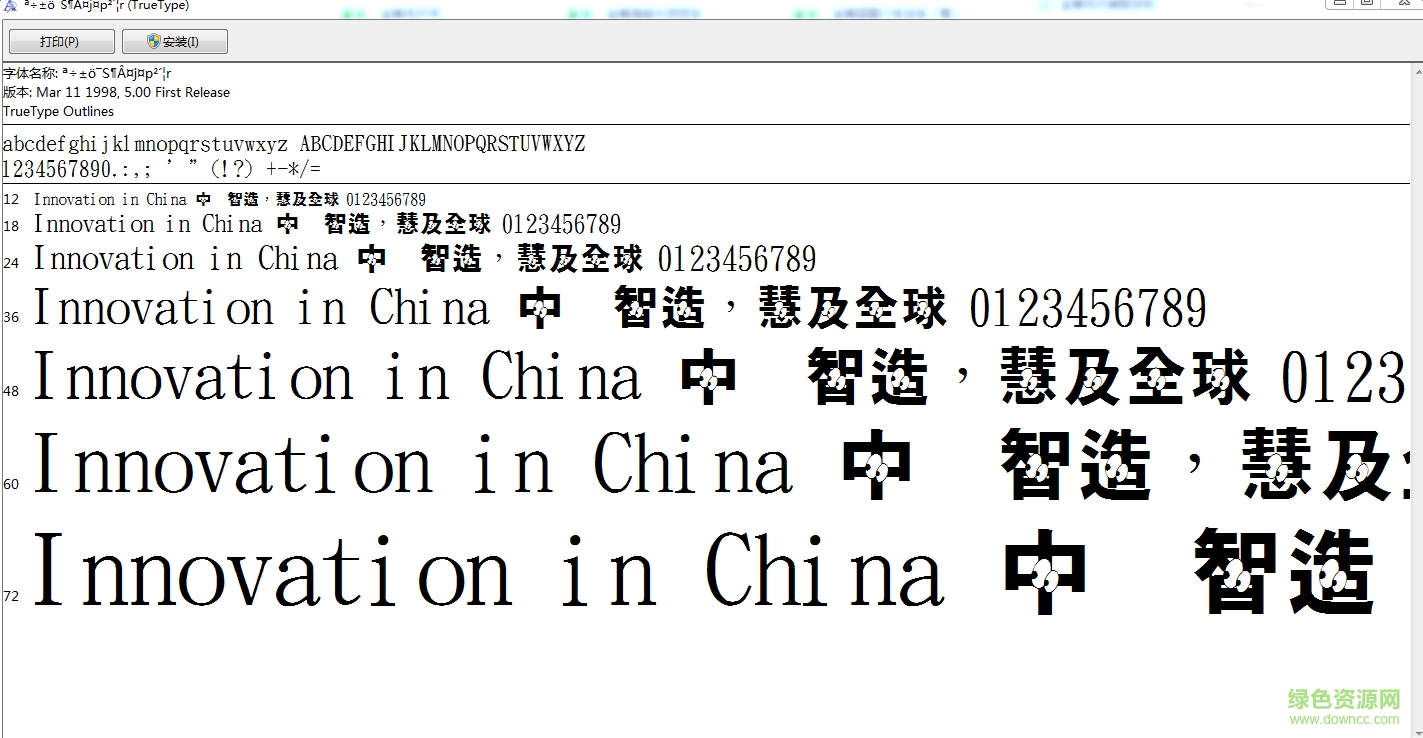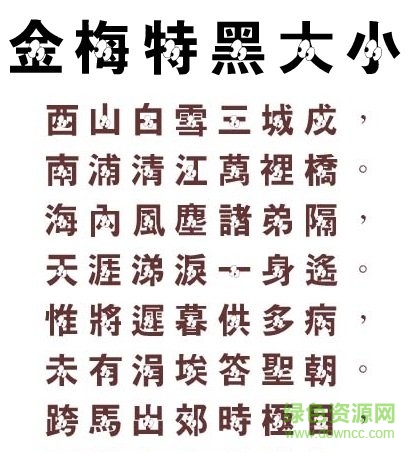
金梅特黑大小眼字是一款非常有個性的金梅字體,字體自帶大小眼效果,可愛又有趣,能讓你的設(shè)計更加增添光彩,字形非常圓潤,喜歡的朋友快來綠色資源網(wǎng)下載使用吧!
好看的美工設(shè)計字體,該字體圓潤研究,看起來頗具正式之感,不過個性之處在于每個字都有一個大小眼的圖案,整體上非常的特別。